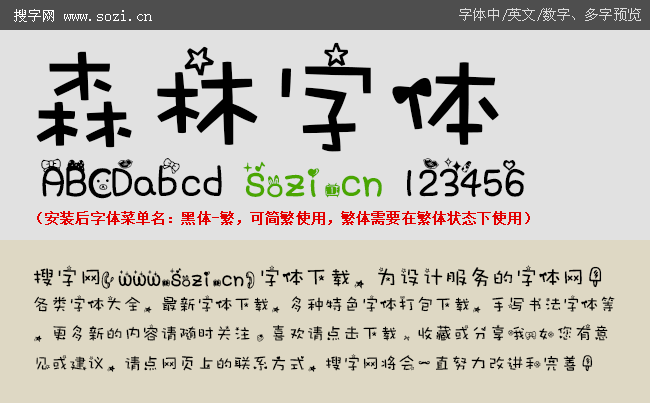
森林字體
搜字網(wǎng)給大家提供一款有趣的手機(jī)中文字體下載。名為森林字體,這款手機(jī)中文字體以黑體為原形,字體結(jié)構(gòu)進(jìn)行了變化,筆畫雖然橫平堅(jiān)直,但通過結(jié)構(gòu)的趣味變化,并且插入了一些卡通圖案,變成了一款十分卡通的POP字形,非常適合喜歡個性的朋友在手機(jī)上安裝使用。